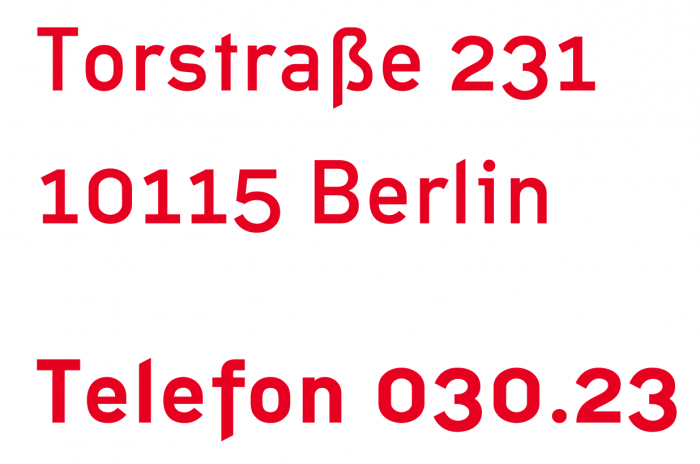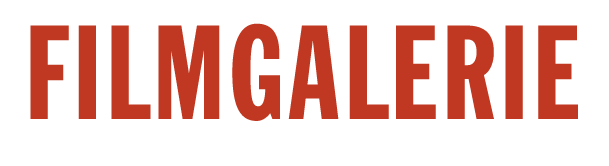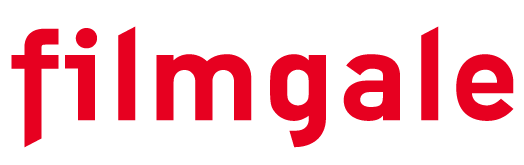
Welche Schrift/en hat die Filmgalerie in Berlin?
Ich muss dringend diese Schrift hier identifizieren für einen Nachdruck. Vielleicht hat jemand eine Idee? Die Kleinbuchstaben sind ja sehr charakteristisch ... gehört der Schrifzug FILMGALERIE auch zur selben Familie?
Danke für die schnelle Info! Die obere habe ich mittlerweile mit hochgeladenen Screenshots bei myfonts.com auch als Franklin Gothic Extra Condensed identifiziert! Bei der anderen Dachte ich auch erst an DIN, aber Interstate passt da schon besser - nur die Zahlen verwirren mich ... ich lad nochmal ein Bild hoch.
Habe jetzt die Schrift als Corporate Font idetifiziert: http://www.typeface2face.com/wolfen.html ...
Ein Gedanke, ohne die Hintergründe zu kennen:
wenn es ein Nachdruck werden soll, warum willst Du die Schrift dann ersetzen? Ist doch nicht umsonst ein Corporate Font, oder? Denkst Du nicht, dass man Dir diese dann auf Nachfrage auch zur Verfügung stellen wird? Schließlich hat man dafür sicher auch einiges bezahlt?!
Noch einen Tipp: Das i sieht aus als ob es aus der OCR-B kommt, dafür kommt der Punt wiederum aus der Interstate. Oder eben aus der FF DIN Alternate. Für alle diese Jugendsünden musste das ß aber schwer büßen. Als ob es in der DIN Mittelschrift noch nicht genug gelitten hat. Da könnte man ja fast Mitleid bekommen. :schonklar: